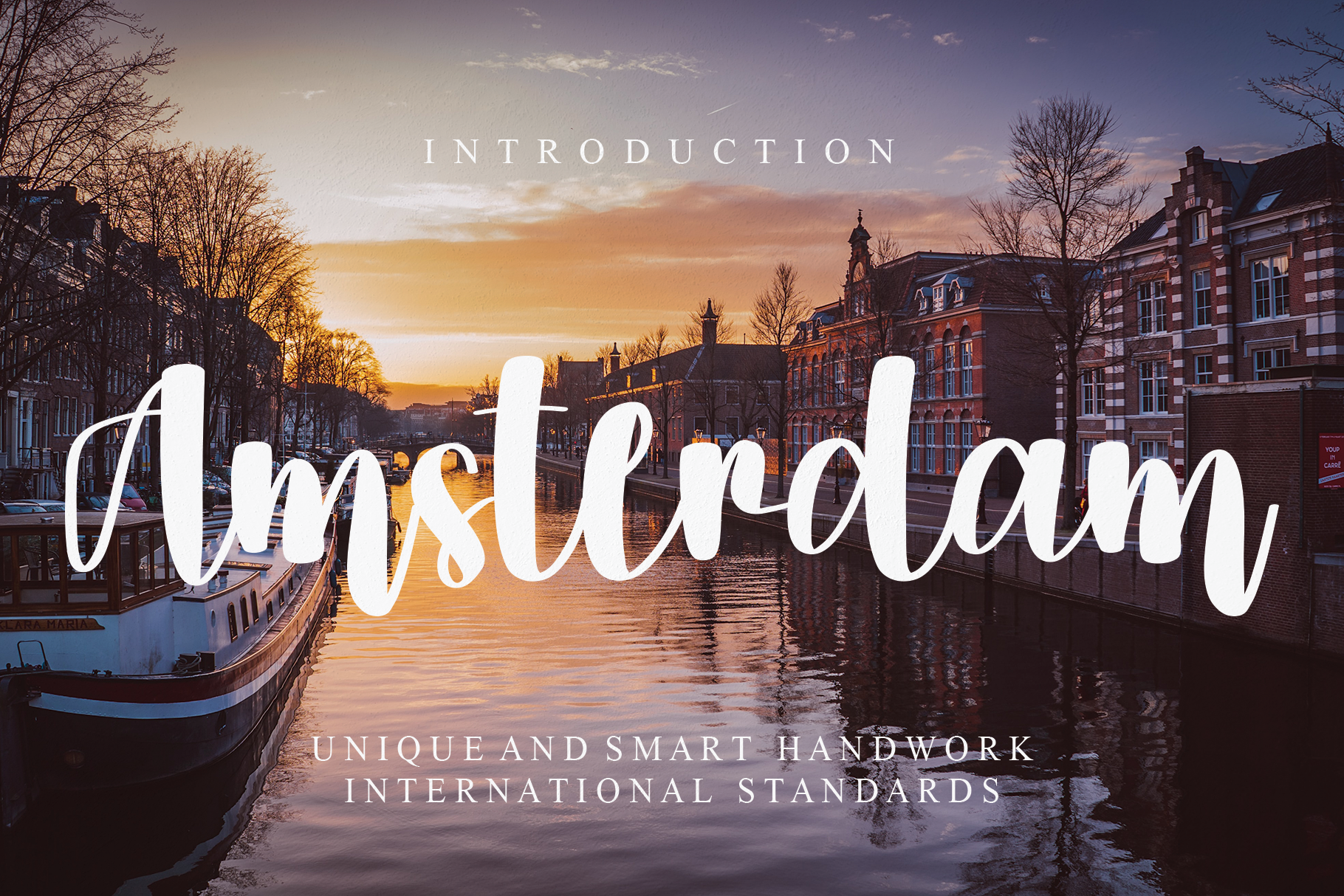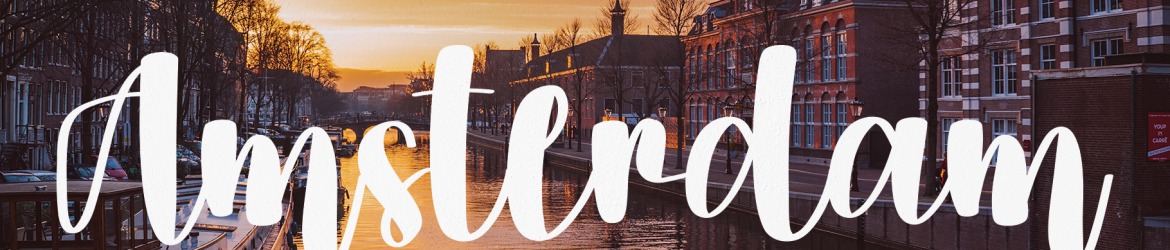
A Amsterdam Typeface é uma elegante caligrafia cuidadosamente elaborada que se destaca pela sua sofisticação e encanto refinado. Este tipo de letra, perfeitamente adequado para qualquer projeto que deseje transmitir um brilho único e distinto, é um verdadeiro complemento perfeito para ambientes requintados e modernos. Com alternativas estilizadas e ligaduras sofisticadas, ela oferece uma variedade de detalhes que tornam a Amsterdam Typeface ideal tanto para design gráfico quanto para editoriais, garantindo sempre o toque delicado necessário para um texto perfeitamente elaborado e único. Seria um prazer adicionar esta fonte à sua coleção, para tornar seus projetos ainda mais impressionantes e profissionais.